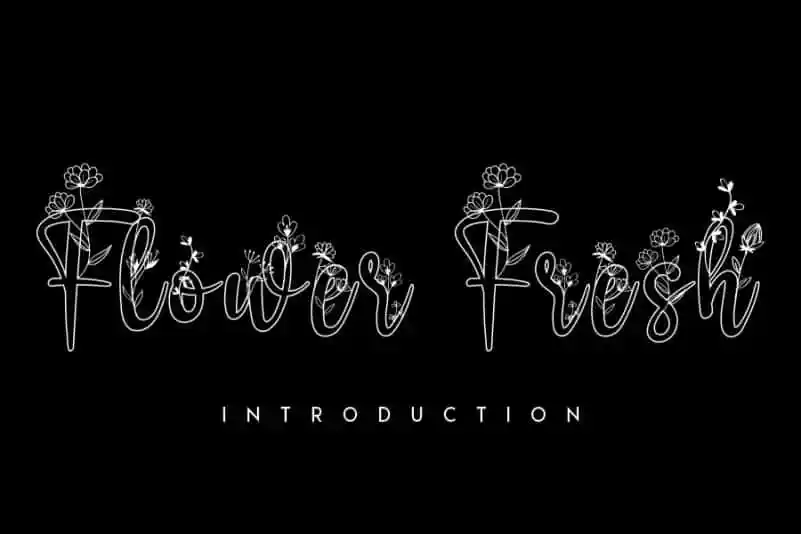
Flower Fresh Display Font – Download Grátis
A fonte ‘Flower Fresh Display Font’ é uma criação meticulosa que oferece um toque elegante ao seu design. Com suas personalizadas personagens florais, ela pode transformar qualquer projeto em algo excepcionalmente especial e único. Suas cores vivas e forma delicada dão ao texto uma aparência de vida real, perfeita para aplicação em variedades de projetos. É ótima para a criação de materiais de escritório, convites casamento, fotografia e embalagens, o que a torna um recurso versátil para todos os tipos de necessidades criativas. A fonte ‘Flower Fresh Display Font’ é perfeita para aqueles que buscam uma forma única de expressar suas ideias em design gráfico.